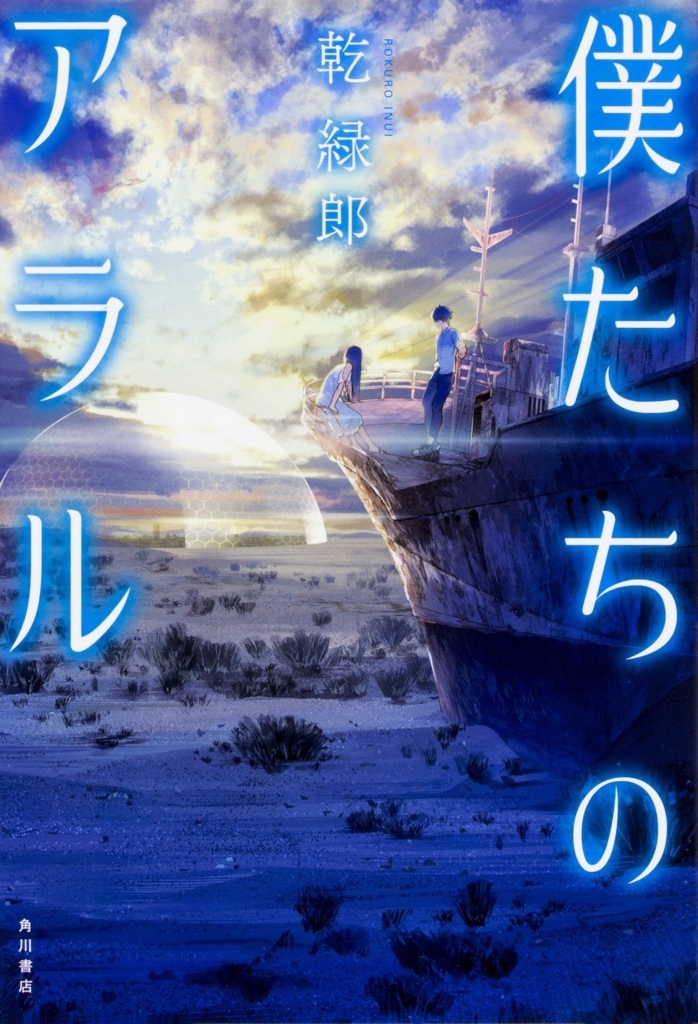
僕たちのアラル
僕たちのアラルのタイトルのフォントに娥眉明朝体が採用
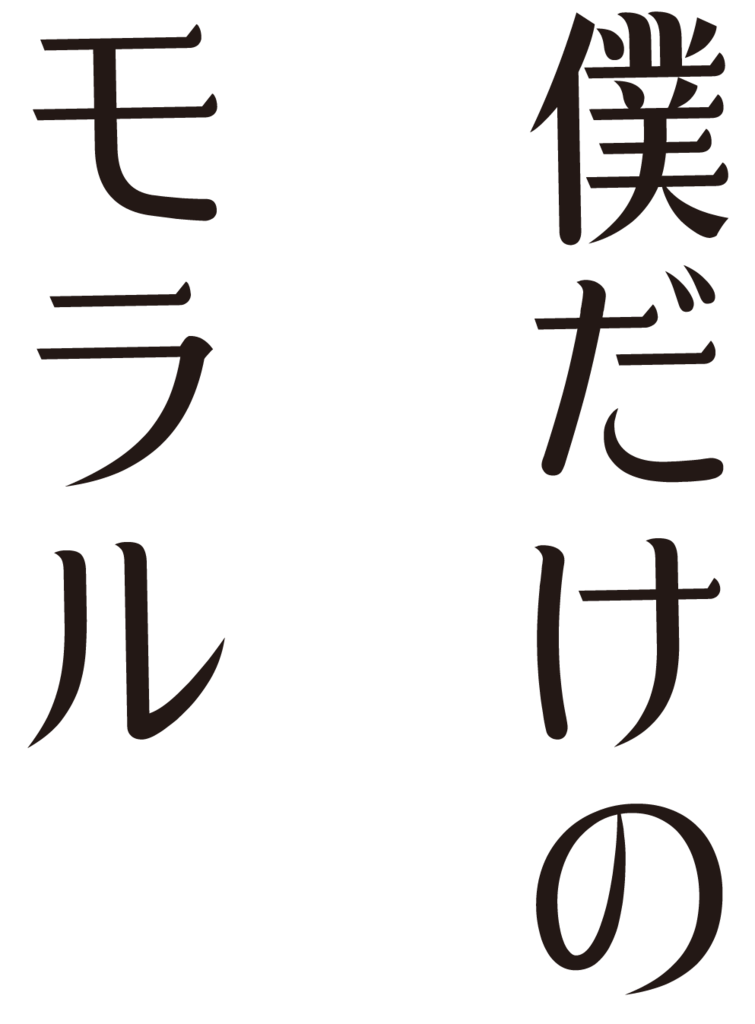
KADOKAWAから刊行された「僕たちのアラル」のタイトルにダイナフォントの娥眉明朝体が採用されている。
娥眉明朝体
通常の明朝体をベースに細長く弧を描いた眉の形をイメージしたストロークから洗練された女性の柔らかさや優しさを表現している。女性用品などのロゴやキャッチコピーに特にオススメの書体であり、女性の美しさを追求した明朝体として、清潔感や高級感ある商品の演出などに優れている。